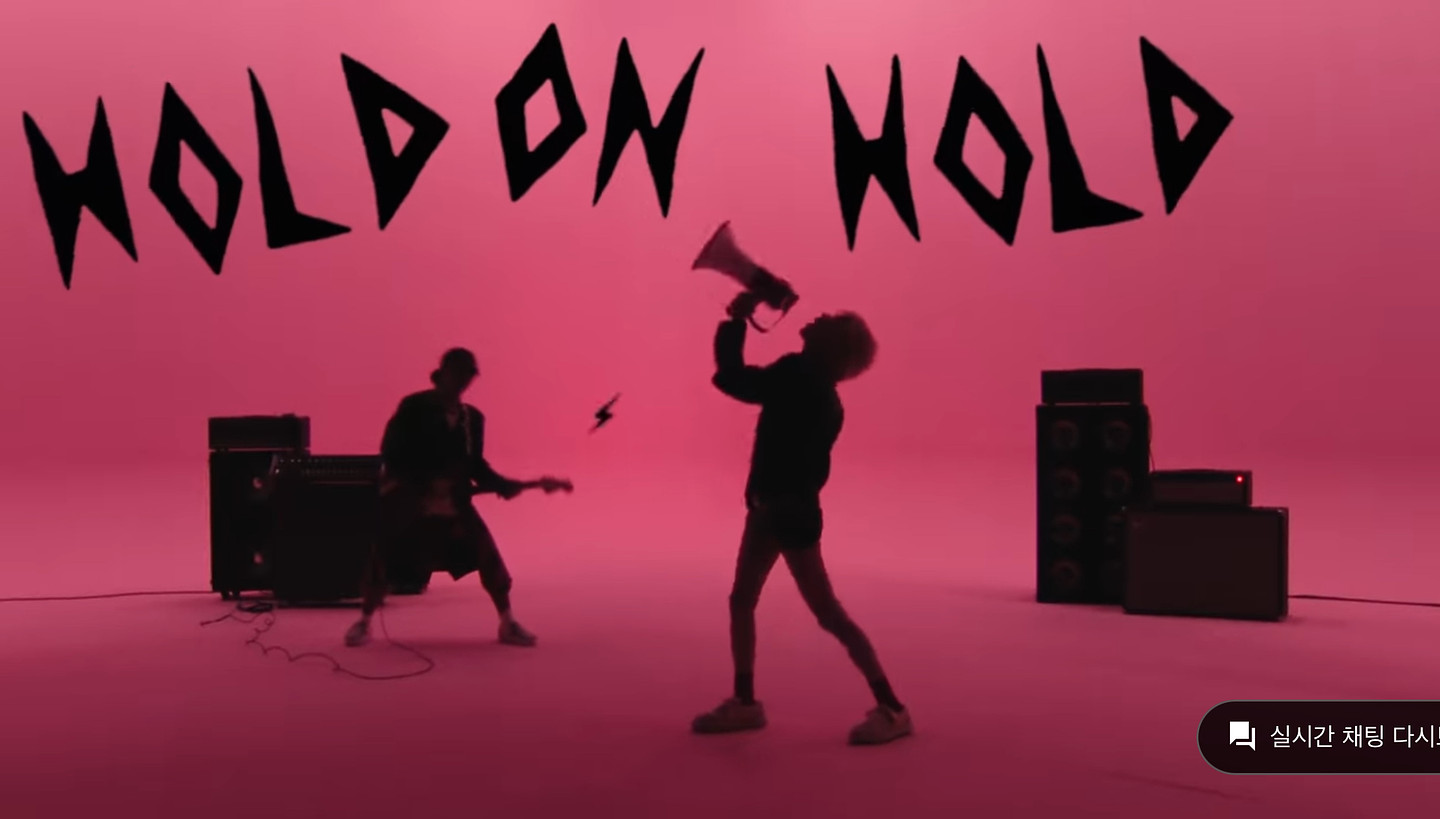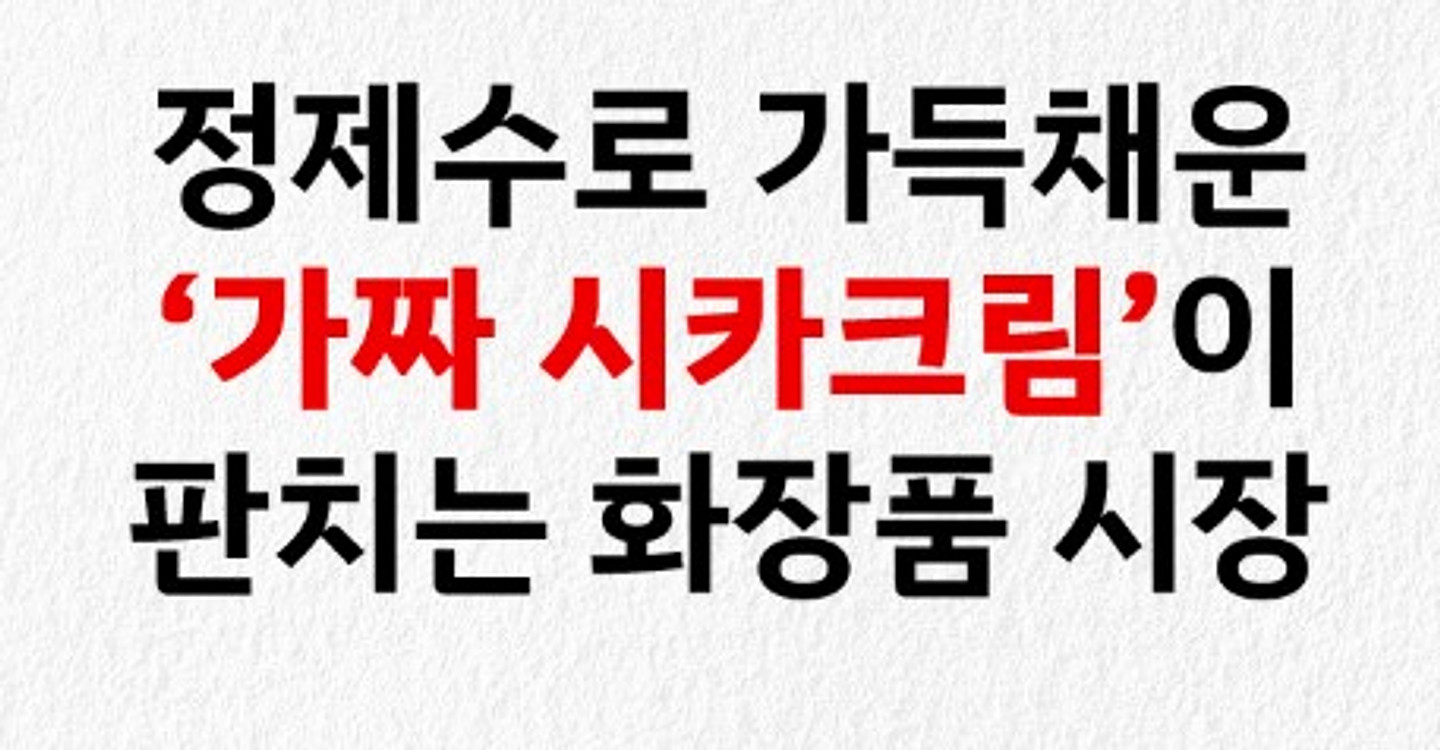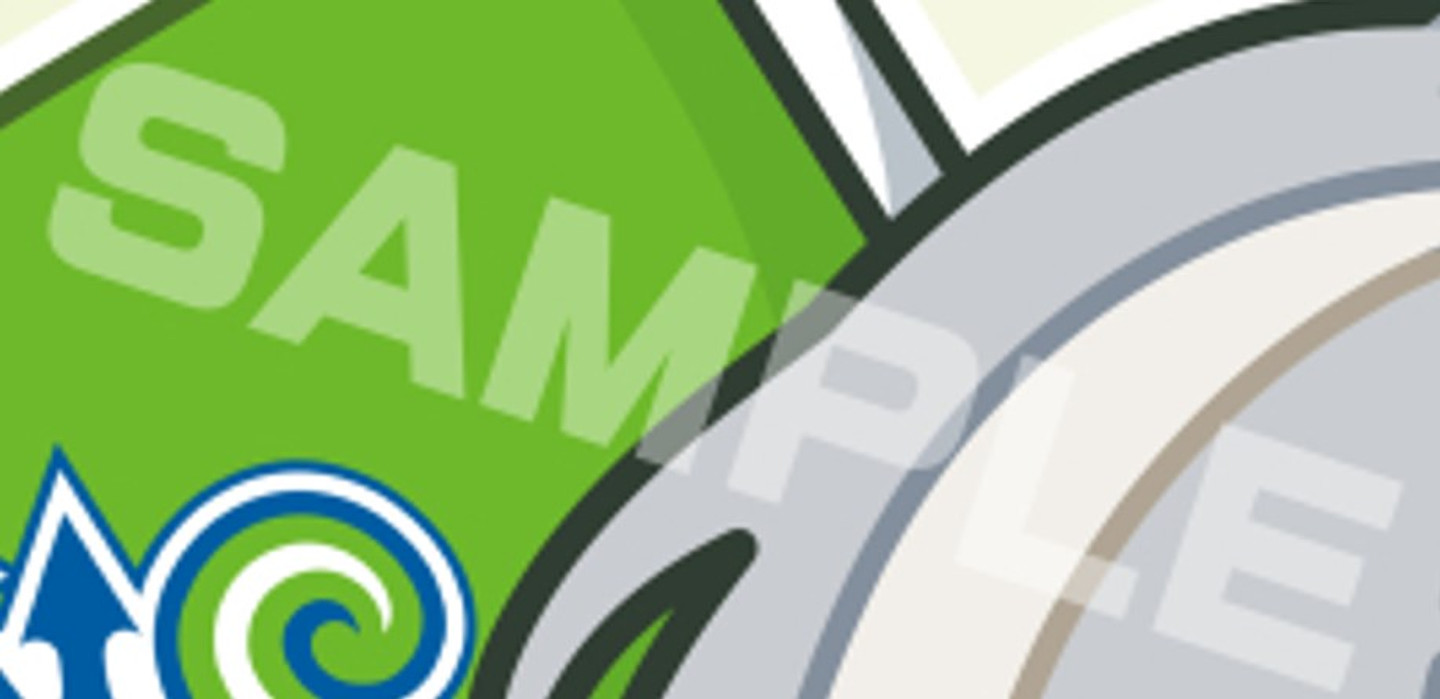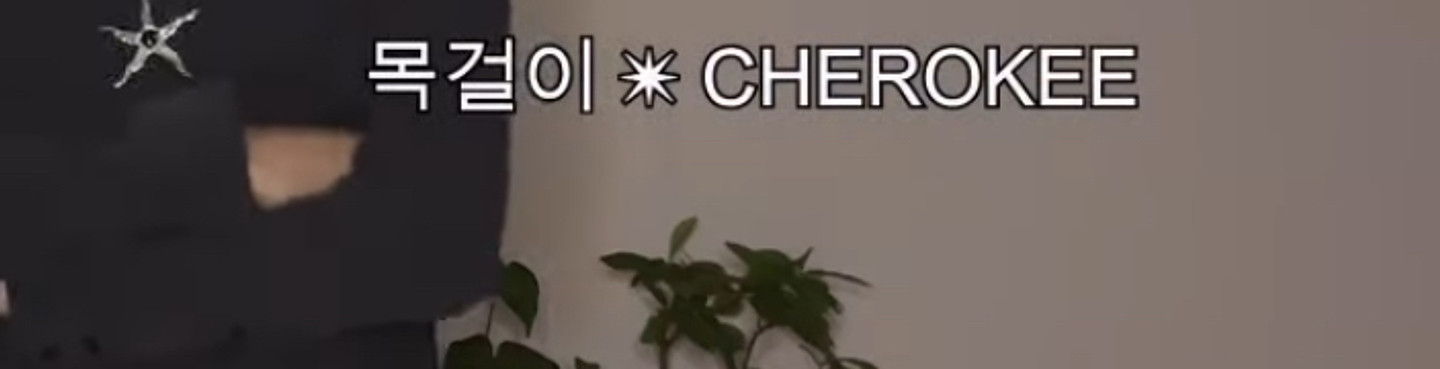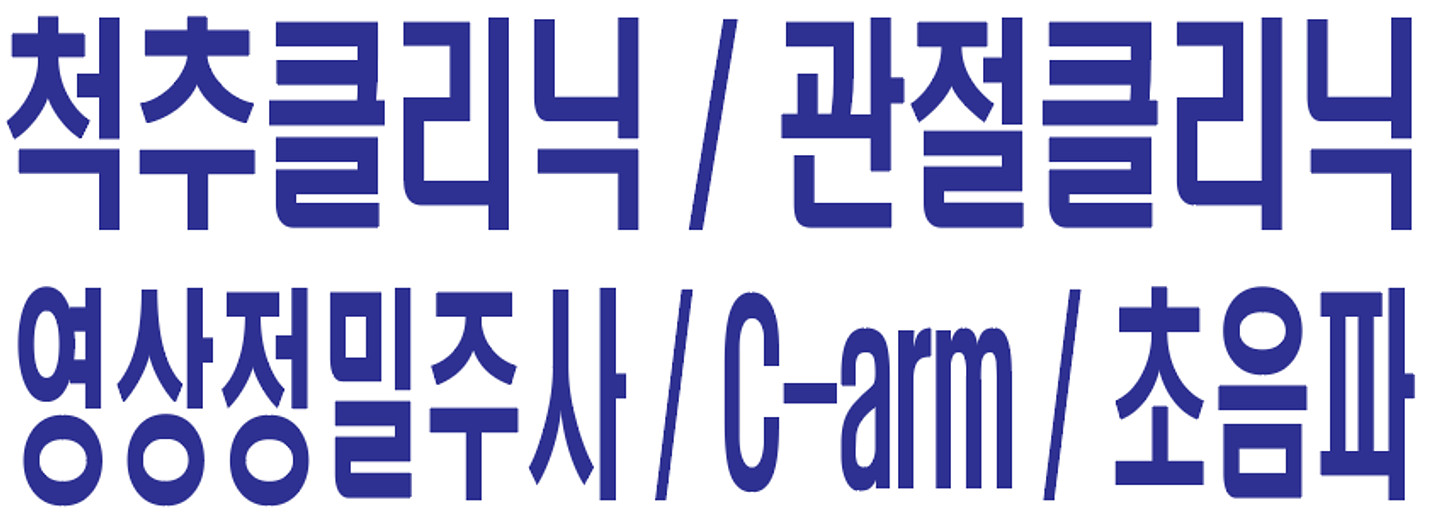
이거 혹시 무슨 폰트일까요?
무슨 폰트인지 알려주세요 😭
이 폰트 무슨 폰트인가요? ㅜㅜ
이 폰트 이름이 뭘까요 ㅠㅠㅠㅠ
혹시 이 폰트 어떤 폰트이신지 아시는 분 계실까요??
어떤 폰트인가요? 알려주시면 감사하겠습니당
이거 무슨 폰트 인가요?ㅜㅜ
삼성 갤럭시 광고인데 큰 글자의 폰트가 정확히 뭘까요. 비슷한 건 보이는데 확실치않아 문의드립니다.
이거 무슨 폰트인지 아시는분 있나요??
이 폰트 뭔지 아시는 분
굴림형식 폰트같은데 해당폰트 알려주세요 ㅠ!
미수반에서 나오는 마크 화면 내 폰트인데 무슨 폰트인지 궁금합니다
“기후동행카드” 폰트랑 중간에 “CLIMATE~” 폰트 무엇인지 알 수 있을까요?
영문 폰트 알고싶습니다!
잘사나보세 유튜브에 자주 나와요. 무슨 폰트일까요?
하룻밤만 재워줘랑 바슷한 상업적 이용 가능 폰트 알려주세요ㅜ
게임 설명부분 어떤 폰트일까요?
본문 청약통장 미리 가입해도 혜택 받을 수 있다고요?의 폰트가 궁금합니다! 아시는 분 계시면 답변 부탁드리겠습니다
해당 폰트가 어떤 폰트인지 궁금합니다!
무슨 폰트인가요?!
상단에 '세계 최대 크루즈로 떠나는' 이 폰트가 뭔지 아시는 분 답변 부탁드려요ㅠ
꾸불림체는 아닌 것 같은데 뭘까요…? 🥹
어떤 폰트인가요?? 제목에 쓰고싶어서 궁금해서 질문드립니다.
무슨폰트인가요...?ㅠㅠ
무슨 폰트인가 알려주세요 부탁드립니다🙏🏻🙏🏻
사이버펑크 2077 엣지러너 오프닝 영어폰트 요 폰트 무슨 폰트인가요? 익숙한데 찾을수가 없습니다 ㅠㅠ
폰트명?
6.25 숫자에 쓰인 글씨체가 궁금합니다 ㅠ
해당 폰트 알려주시면 감사하겠습니다!!
글씨가 동글한데 반듯하다 궁금해요 ㅠㅠ
이 폰트 무슨 폰트인지 알고 싶습니다. 아시는 분 알려주세요~~~제발....
인스타보다가 폰트가 예뻐서요ㅠㅠ 뭘까요
폰트가 뭘까요??
무슨폰트죠?
고재영씨가 평소에 사용하는 이 폰트가 뭘까요?
이 폰트 무슨 폰트인지 아시는 분 계신가요?? ㅠㅡㅠ
제발 알려주세요ㅠㅠ
'울퉁불퉁 생긴 크랙 자막'이라고 적힌 폰트 뭔지 알려주세요 ㅜㅜ!
이거 EBS 개념완성 같은 곳에 보면 이런 모양의 숫자 보일 텐데 이 폰트가 뭔가요?
이 글꼴 무엇일까용?
이 폰트랑 비슷한 느낌의 무료폰트를 찾고있는데 있을까요?
MBC 옛날로고에 있는 폰트인데 부분 수정된 폰트네요. 한글 문화방송체가 아닌 "Banco"라는 폰트 알려주세요
안녕하세요 이 폰트 혹시 아시는 분 계실까요 ? 너무 궁금한데 찾다가 도무지 찾기가 힘들어서 여쭤봅니다 !
이 글꼴 좀 알려주세요
법률 문서에서 나왔는데 폰트가 궁금합니다...
글꼴 찾을 수 있을까요?
첨부된 글자의 윗줄과 아랫줄의 폰트 디자인과 크기 알려주세요.
mbc로고 폰트가 뭔가요
아래쪽 영문 dap mall에 사용된 폰트가 무슨 폰트인지 알고싶습니다. 특히 ma자가 예시이미지와 비슷한 폰트가 있을지요?
이 폰트 무슨 폰트일까요? 바로 만들어야 해서 급합니다
폰트 뭘까요??
이 서체가 무슨체에요??
이 폰트 뭔지 알 수 있나요?
무슨 폰트인가요 ?
무슨 폰트일까요ㅠㅠㅠㅠㅠ
이 폰트 무슨 폰트인지 알수있을까요?